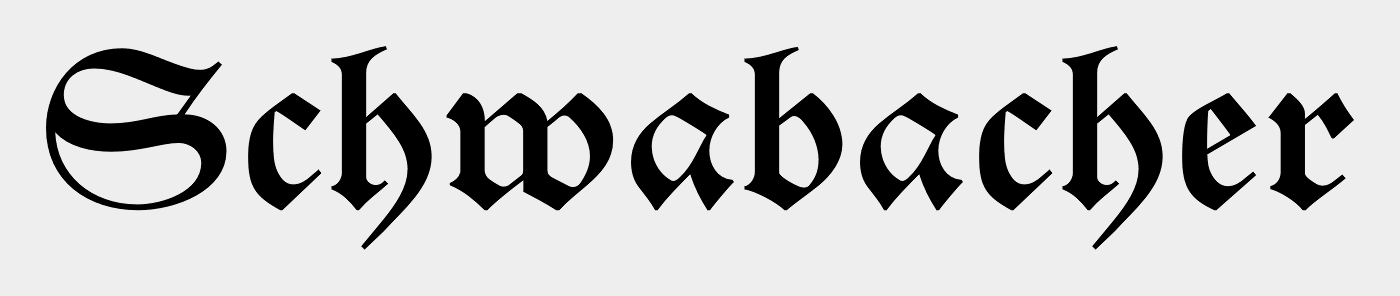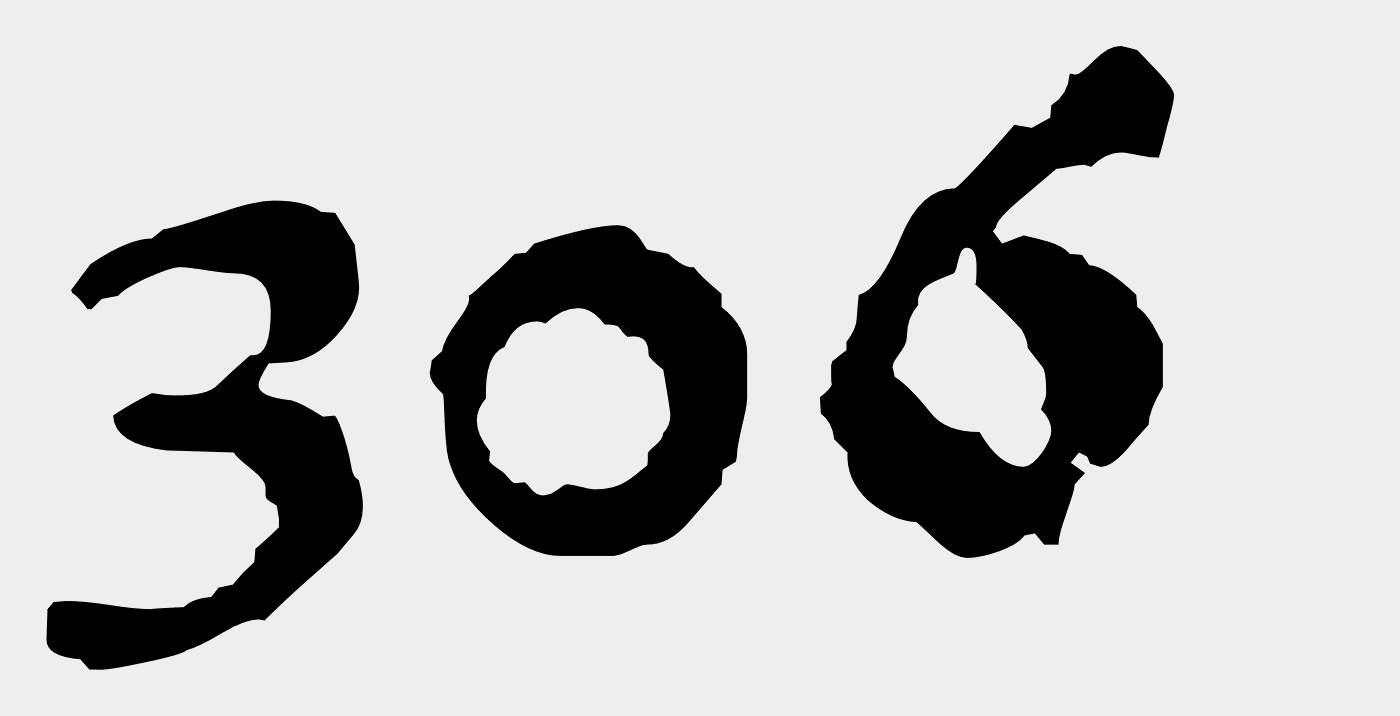
Welche Schwabacher mit Mediävalziffern gibt es?
Falles überhaupt eine gibt … :-?
vor 17 Stunden schrieb Kathrinvdm:
Ähm … warum sehen die denn so zerstört aus? Ist MyFonts kaputt?
Das soll wohl das Druckbild simulieren. Mag in kleinen Schriftgraden ganz passabel aussehen, im gezeigten Muster ist’s eher das Grauen … ;-)
(Mir ging’s gar nicht um die Qualität, sondern nur um die Frage, ob es überhaupt Schwabacher mit Mediävalziffern gibt. Das war eine Frage eines Bekannten, bei der ich passen musste.)
Na, dann ist die Frage ja geklärt. Also nächste Frage:
Gibt es eigentlich einen Weg, im Schriftmuster von MyFonts die OSF anzuzeigen, wenn diese nicht die Standardziffern sind? (Ich habe es nicht geschafft.)
Das war eine Frage eine Bekannten, bei der ich passen musste.
:nana:Das kannst Du uns nicht erzählen! Du bist doch unser Fuchs!
vor 5 Minuten schrieb Thomas Kunz:
Na, dann ist die Frage ja geklärt. Also nächste Frage:
Gibt es eigentlich einen Weg, im Schriftmuster von MyFonts die OSF anzuzeigen, wenn diese nicht die Standardziffern sind? (Ich habe es nicht geschafft.)
vor 6 Minuten schrieb Thomas Kunz:
Gibt es eigentlich einen Weg, im Schriftmuster von MyFonts die OSF anzuzeigen, wenn diese nicht die Standardziffern sind? (Ich habe es nicht geschafft.)
vor 6 Minuten schrieb Kathrinvdm:
:nana:Das kannst Du uns nicht erzählen! Du bist doch unser Fuchs!
Gebrochene Schriften sind eindeutig ausgenommen, ich kann keine Fraktur von einer Schwabacher unterscheiden. :aschehaupt:
vor 3 Stunden schrieb Kathrinvdm:
Ähm … warum sehen die denn so zerstört aus? Ist MyFonts kaputt?
Da hat einfach nur jemand einen kleinen Druck auf rauem Papier als Vorlage genommen, das eingescannt und das durch automatische Vektorisierung gejagt.